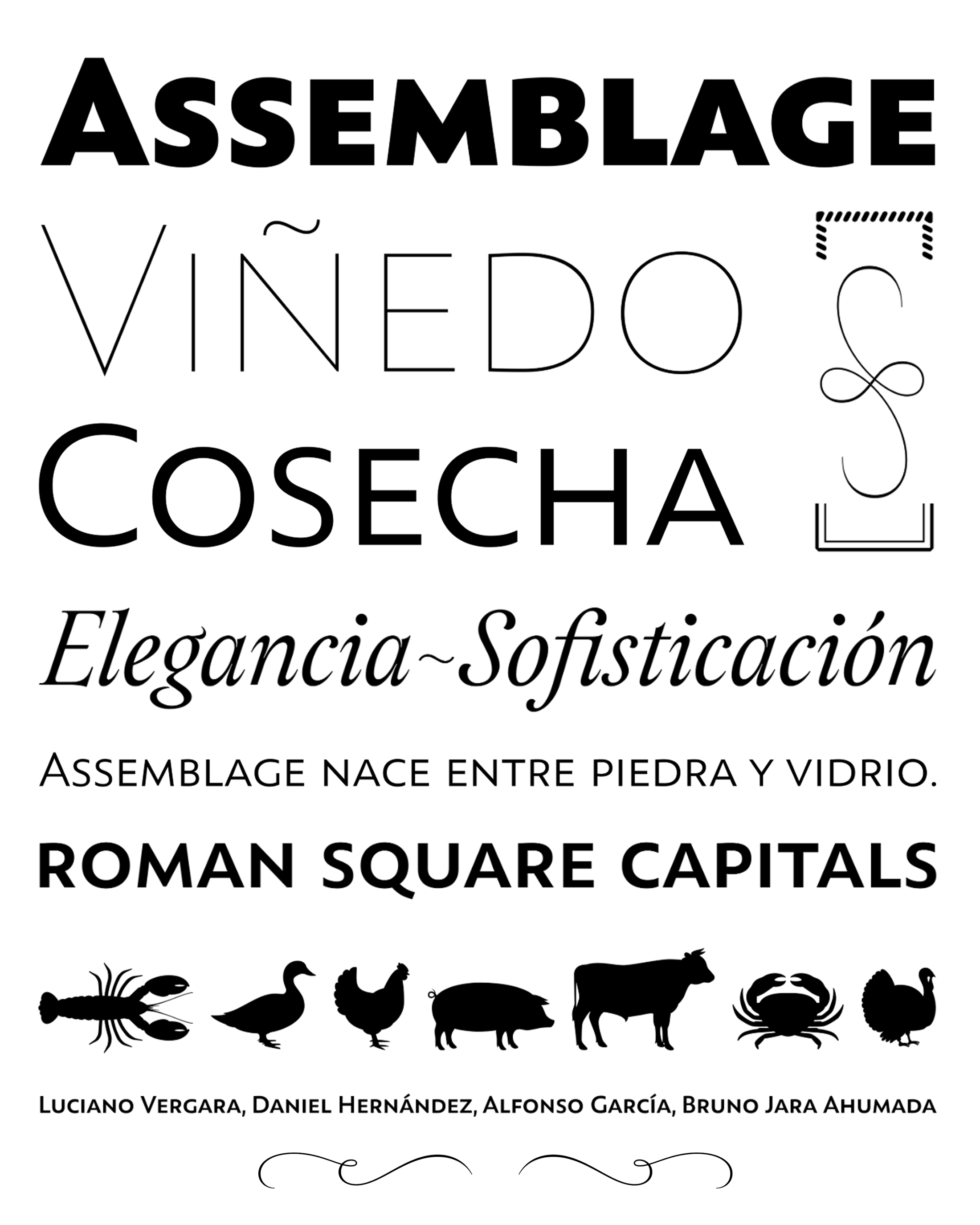
| Año | 2016 |
| Créditos | Luciano Vergara, Daniel Hernández, Alfonso García, Bruno Jara Ahumada |
| Descripción | Montaje Diseñado por Daniel Hernández, Alfonso García, Bruno Jara Ahumada y Luciano Vergara. Gracias a Pedro González por su contribución en la fase inicial del proceso de diseño. Assemblage es un tipo de letra -inspirado en las mayúsculas cuadradas romanas- que se presenta en 6 pesos diferentes, desde el fino al negro. El fondo del tipo de letra lo hace muy adecuado para marcas, textos cortos, títulos y composiciones complejas, gracias a su versión en cursiva. A diferencia de otras fuentes conservadoras, Assemblage incluye una versión en cursiva con un aspecto basado en las tipografías Elzeverian y Dutch Barroque, lo que aporta a la fuente un toque extra de elegancia, resultando en un diseño muy agradable. La familia se creó especialmente para etiquetar botellas de vino y envases en general. Assemblage es una colección tipográfica compuesta por una Sans Serif y una versión cursiva de rasgos clásicos. La familia se presenta en 6 pesos e incluye ligaduras, mayúsculas y versalitas, además de 3 conjuntos de versalitas más pequeñas para distintos tipos de composición. La versión cursiva -con fuertes rasgos decorativos- incluye guiones. Assemblage también incluye un juego de dingbats, especialmente diseñados tanto para envases como para publicaciones o marcas. La versión Sans contiene 979 caracteres y la cursiva, 620. Assemblage admite 212 idiomas diferentes y sus características OpenType incluyen ligaduras, cifras semiantiguas, 3 conjuntos de versalitas ornamentales (en la versión Sans), guiones, formas finales y alternancias en la versión cursiva. |
| Familia(s) | Thin, Light, Regular, Semibold, Bold, Black, Italic, Dingbats, Ornaments |
| Estilos | 9 |
| Glifos | mayor que 1000 |
| Set | Especializado |